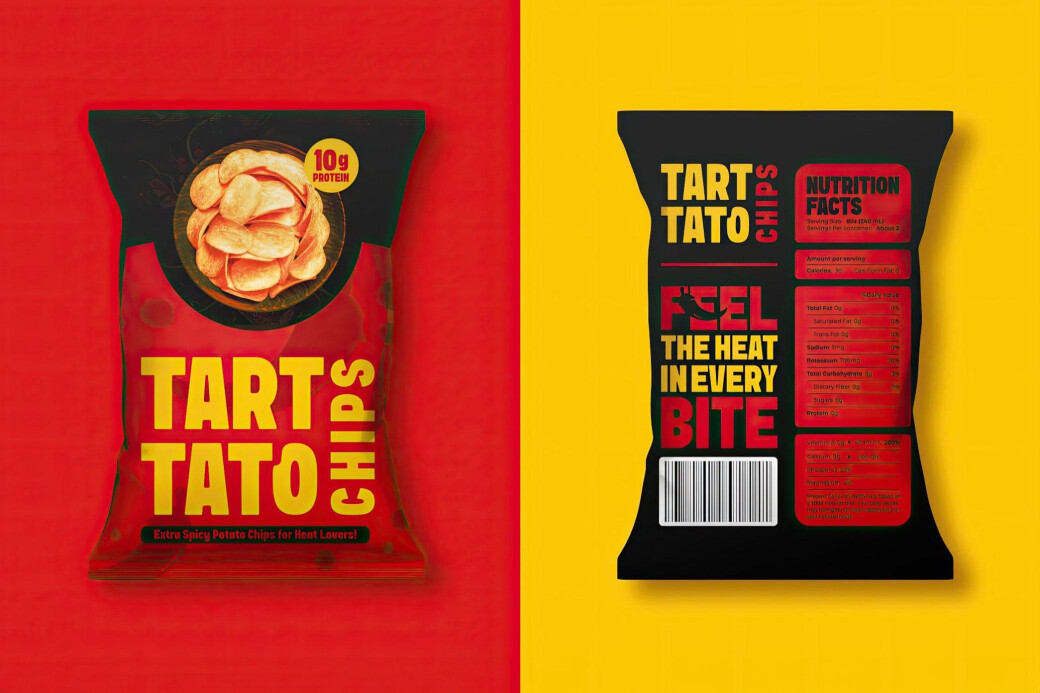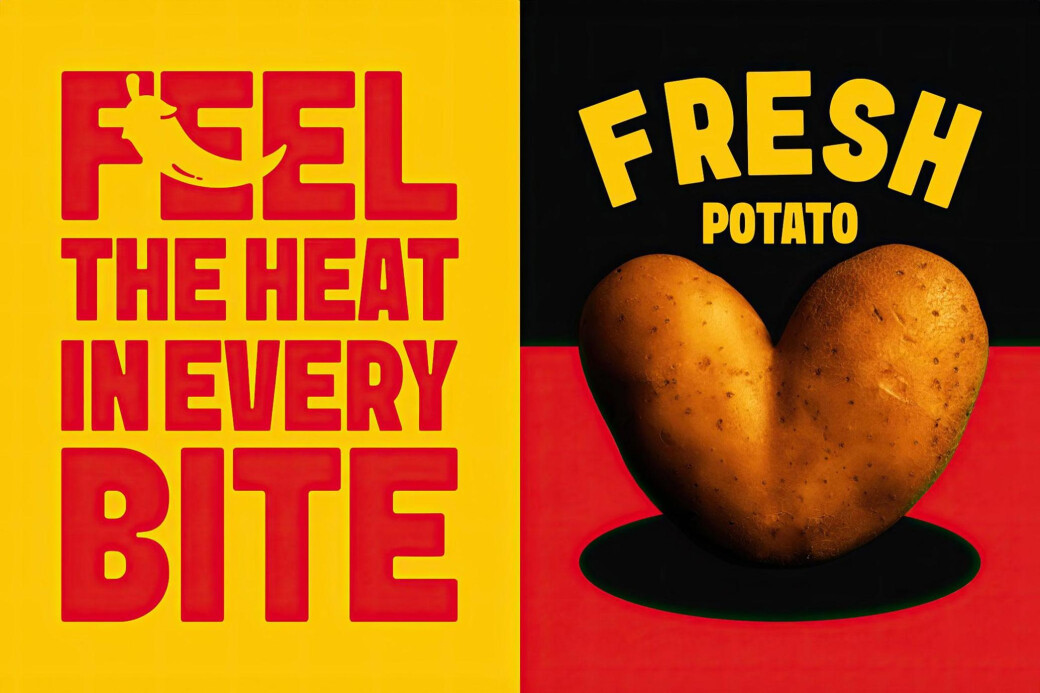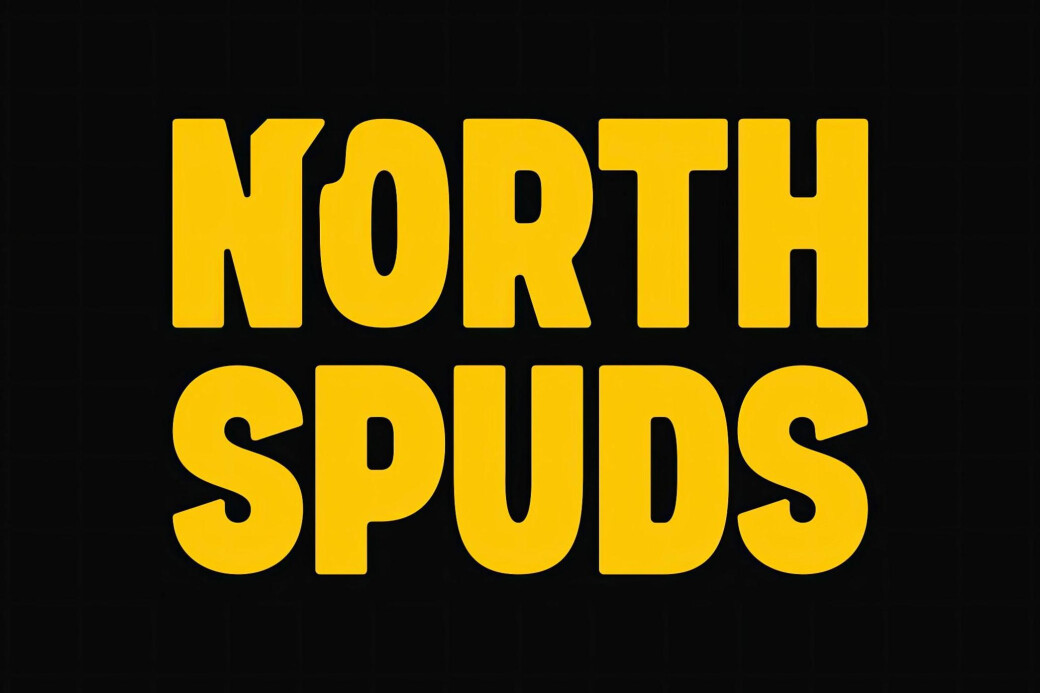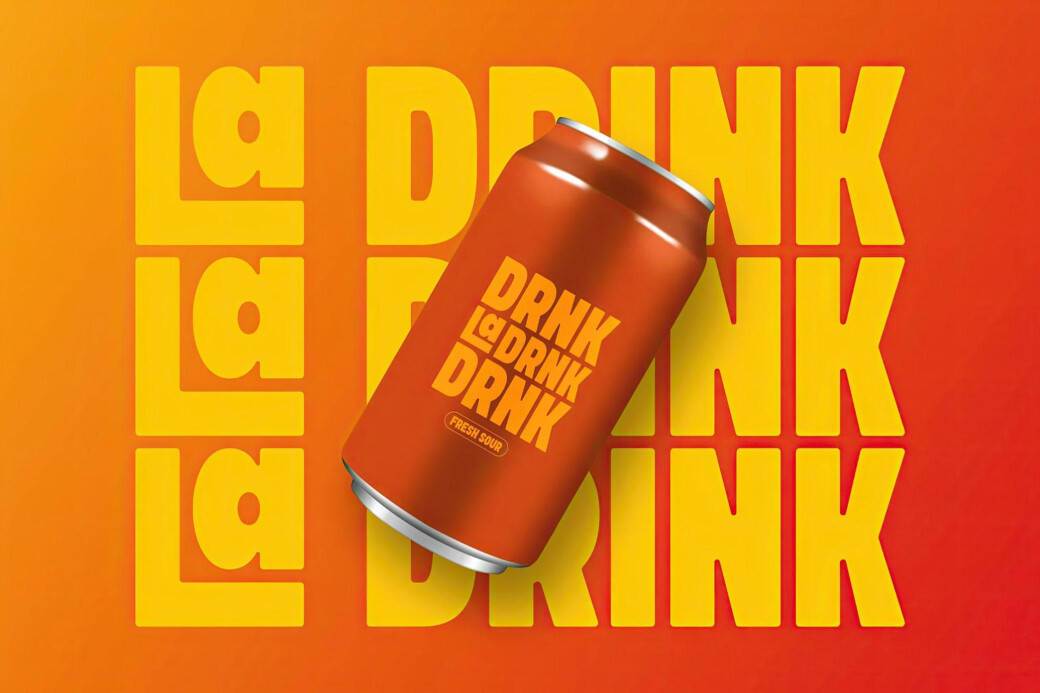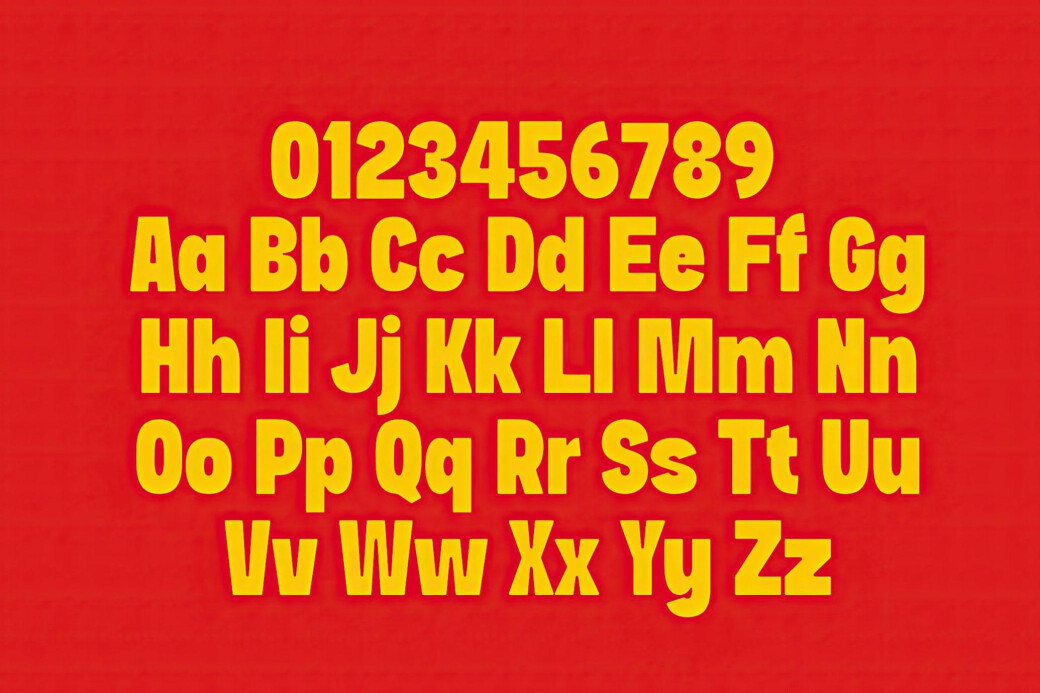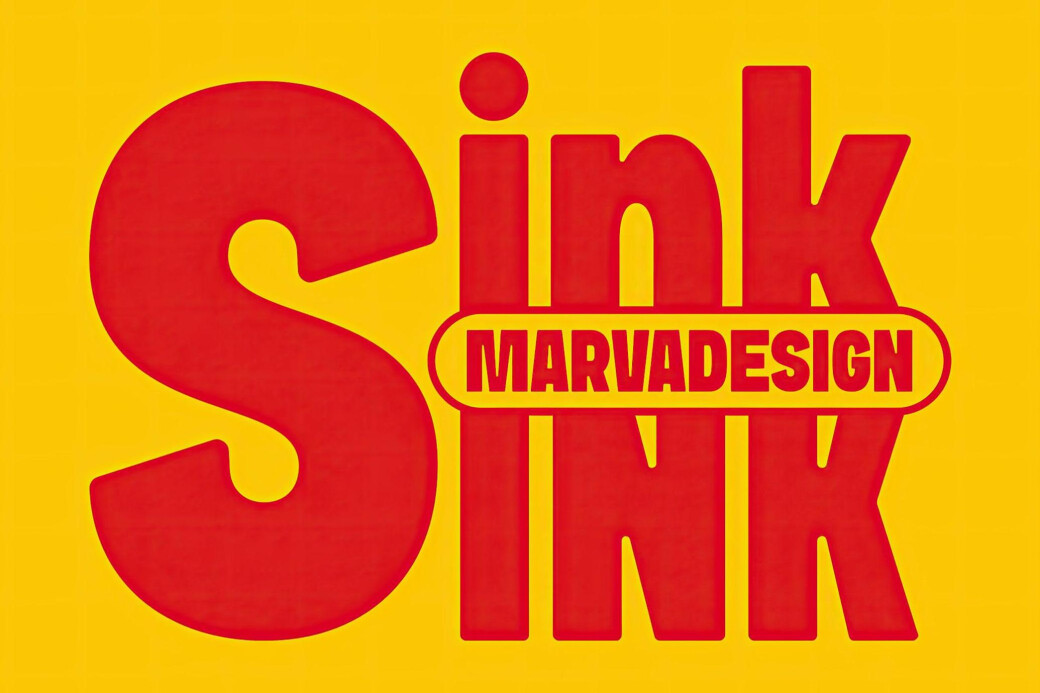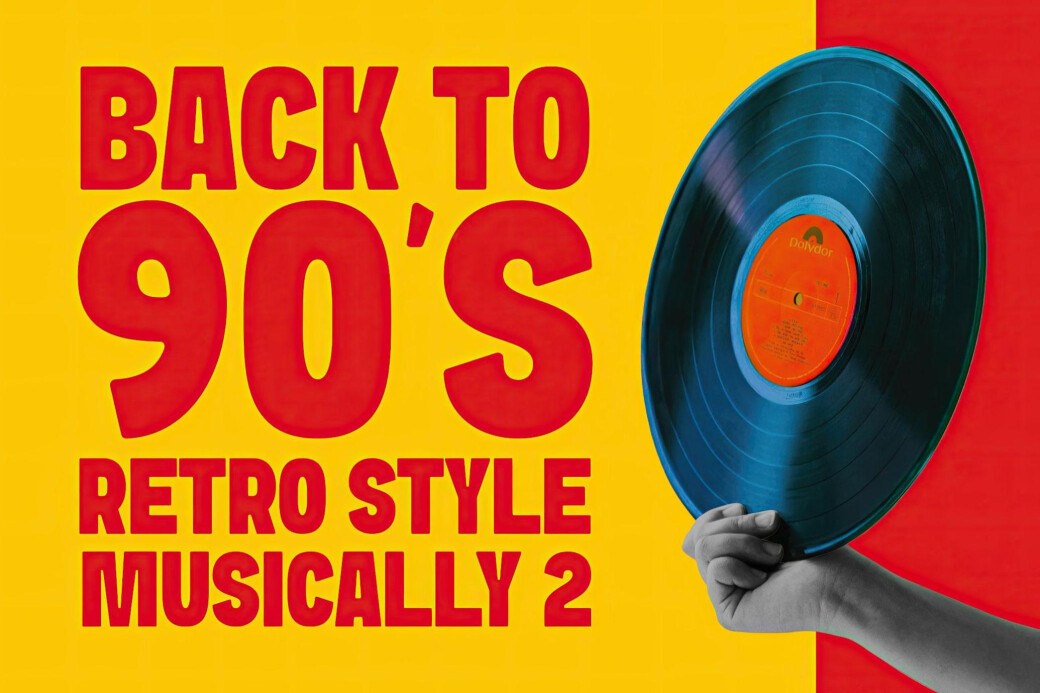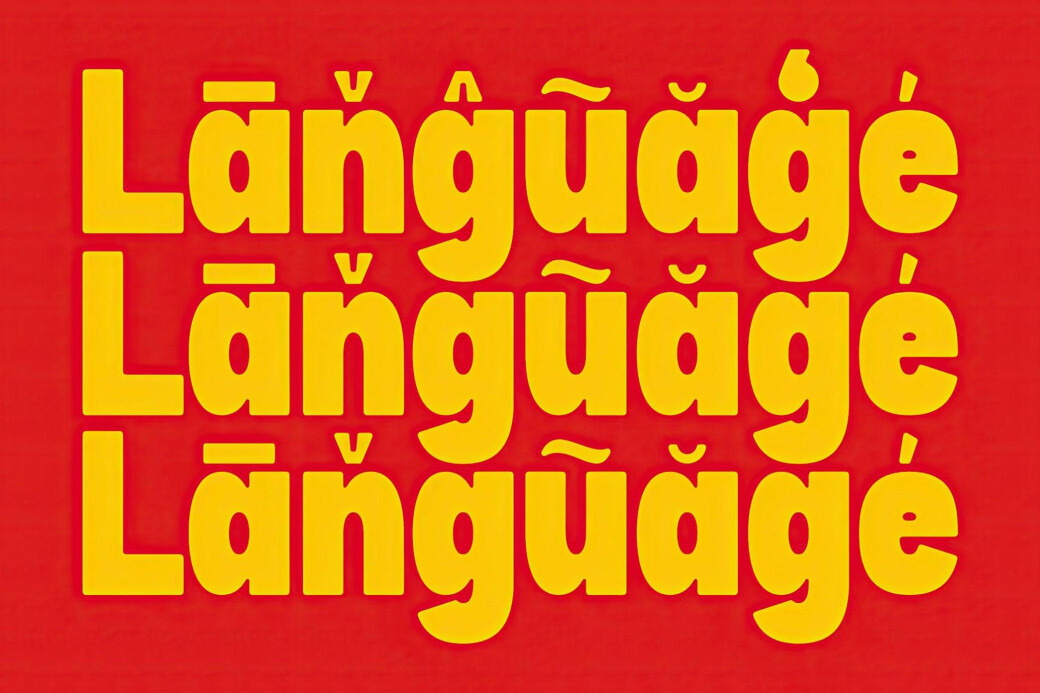
«Большой, смелый и неподдающийся игнорированию» — именно так можно описать шрифт SINK. Это то, что вы почувствуете, как только увидите его. Корни SINK уходят в эстетику быстроразвивающегося фастфуда 70-х, с его крупными рекламными буквами и классическим дизайном упаковки. Этот шрифт излучает ретро-уверенность с современным оттенком.
Шрифт включает:
- Большие и маленькие буквы
- Числа, знаки препинания и поддержку нескольких языков.
С его помощью вы легко создадите яркий проект для брендинга, постеров и других смелых заявлений.